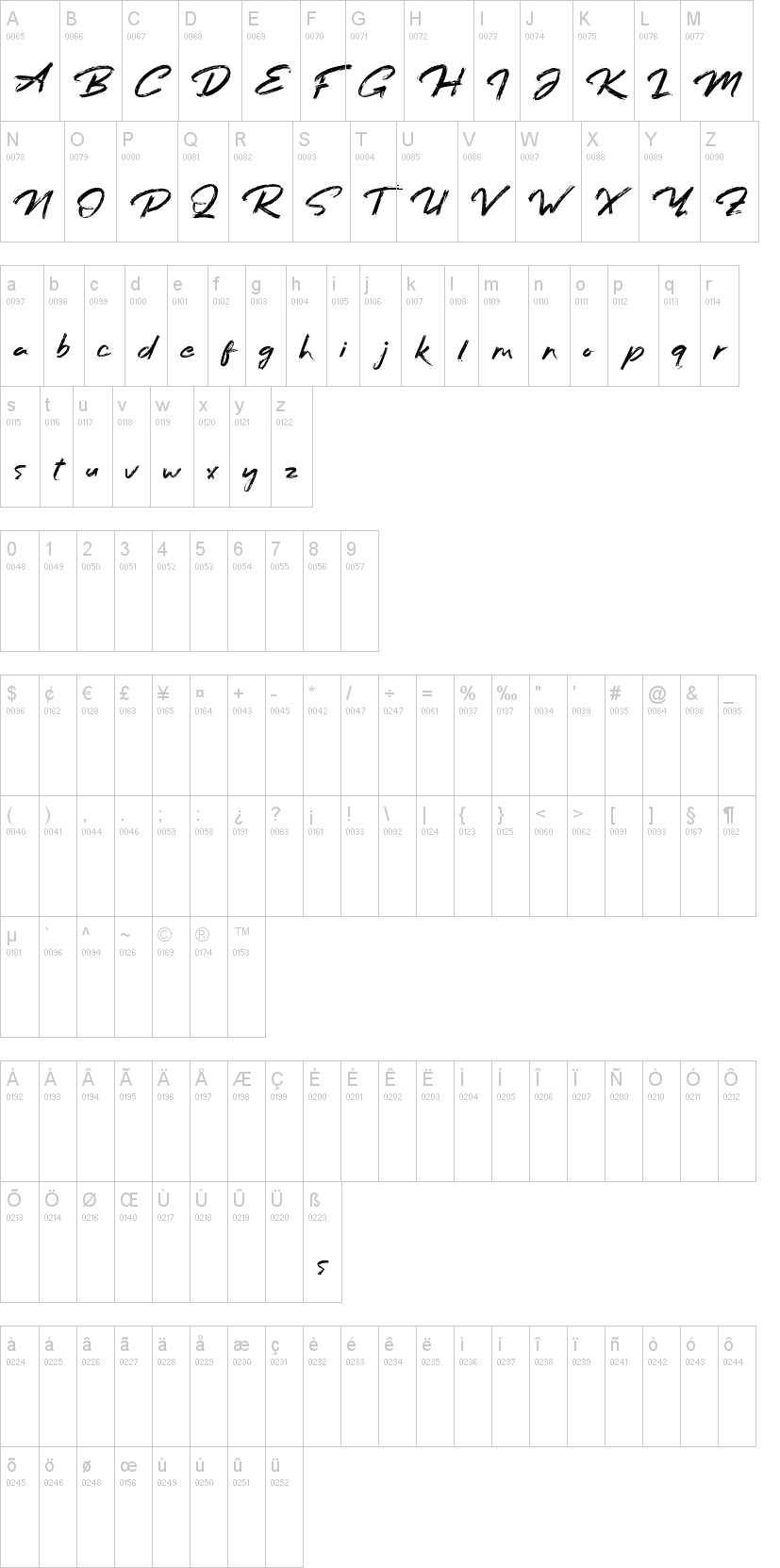
Bafora
Bafora 是一款受到爱尔兰民间艺术和传统文化启发的特殊字体。它既有简单的表现形式,又有复杂的细节,有着多样的表达形式。它具有爱尔兰传统文化的独特风格,同时也具有现代感,能够为您的设计带来活力和创意。Bafora 字体可以用于多种场景,从网页标题到广告标语,从海报到宣传单,都能够发挥出它独特的魅力。
Bafora是一款非常不错的手写艺术字体,具有很好的视觉感,适合于文化类的宣传设计、商业类品牌的广告和产品包装设计以及个性化文字排版等较多场景。